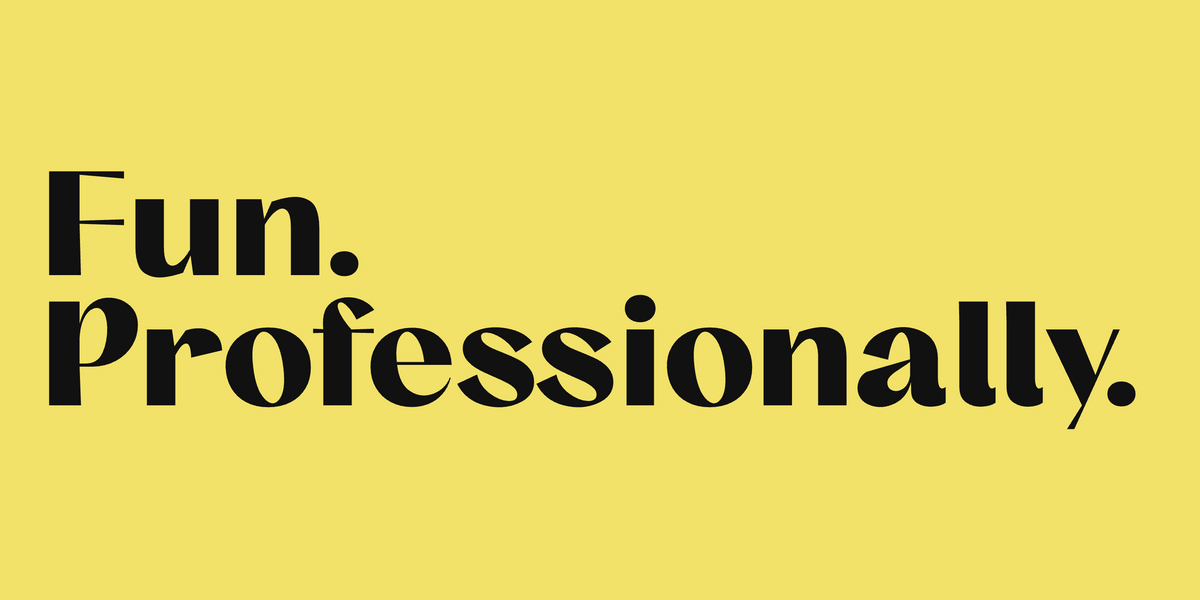
10 fuentes divertidas para proyectos creativos con una personalidad alegre
Fun. Professionally. Set in Rati by Mojomox
Las letras puntiagudas en una fuente pueden parecer más divertidas.
1. Bool, fuente puntiaguda y en negrita
La tipografía Bool es diferente de las fuentes divertidas habituales. A primera vista, este tipo de letra parece relativamente geométrico, pero veámoslo más de cerca.
Algunos de los contadores de la fuente están desplazados, por ejemplo, los contadores de la letra B están más cerca del centro y de la derecha, lo que le da un aspecto un poco bizco y divertido. Las barras transversales del medio son más delgadas que el ancho total del trazo, lo que le da al tipo un carácter de dibujo animado muy atractivo.
Algunos ejemplos son las letras G, E y F. Por último, la barra transversal de la A es más baja de lo habitual, lo que la convierte en una tipografía agradable. Estas divertidas características son más pronunciadas en los grosores de fuente más negrita, desde SemiBold hasta Black.
Las letras que terminan en un trazo ascendente parecen más amigables.
2. Fuente de encaje, estilo de escritura monolineal
Lace es una tipografía de estilo manuscrito. Los grosores de fuente más finos, como ExtraLight y Light, tienen una calidad de bolígrafo, mientras que los estilos más atrevidos presentan un trazo estilo marcador.
Cada letra se dibuja en una línea (estilo monolineal) creando divertidos bucles.
Muchas de las letras de este tipo de letra terminan en un trazo ascendente que crea una apariencia amigable.
También hay disponible una versión redondeada de esta fuente, Lace Rounded.
Las letras que tienen una forma ligeramente diferente a la normal se destacan y parecen más divertidas.
3. Sway, fuente futurista ondulada
La fuente Sway es un alfabeto completo en letras mayúsculas únicamente. Este tipo es excelente para textos de carteles, pero no es particularmente fácil de leer como cuerpo de texto. Sway tiene un estilo futurista y moderno, pero al mismo tiempo se ve moderno y divertido. Las letras de Sway están dispuestas en ángulos particulares, lo que les da un patrón de diseño que las hace fáciles de usar para logotipos.
Las formas redondas en una fuente son más divertidas.
4. Ratón, tipo divertido de estilo acuático.
Vole es una tipografía en mayúsculas y minúsculas, que incluye el alfabeto latino extendido. Su característica principal de diseño son los redondeos que permiten que los trazos se fusionen entre sí, lo que le da al tipo un toque de tinta.
En general, se trata de una fuente geométrica con una estética tipográfica Bauhaus. Por ejemplo, a las letras b, g, n y r les faltan los trazos generalmente extendidos, lo que le suma un toque redondeado y divertido a toda la tipografía.
Vole es ideal para la marca de los niños y es especialmente lindo cuando se escribe todo en minúsculas.
Los puntos i más grandes brindan una sensación amigable
5. Bau, fuente modular redondeada
La fuente Bau es la fuente predecesora de Vole (ver arriba). Las letras de la tipografía se basan en círculos, lo que le da un carácter modular y divertido.
Sus i-dots son más grandes que los puntos estándar, lo que aumenta la facilidad de uso del diseño. Consulta todos los tamaños de fuente, desde superdelgados hasta muy gruesos, aquí .
Las fuentes con apariencia manuscrita son más divertidas.
6. Skay, fuente de burbuja en mayúsculas
Skay es otra fuente de estilo manuscrito que viene en nueve grosores. En particular, sus grosores más audaces se consideran divertidos y amigables, además de tener una personalidad orgánica. Un ejemplo famoso que utiliza este tipo de fuente es el logotipo de Skims.
Este tipo solo tiene letras mayúsculas y números y es parte de la familia de fuentes de burbuja .
Diferentes fuentes
7. Slye, fuente divertida con corte central
Este tipo de letra no es fácil de leer como texto, pero es genial y diferente. Una fuente como Slye es ideal para logotipos, carteles y titulares. Muestra una personalidad que quiere ser audaz y destacarse.
Es divertido mezclar esta fuente con otra. Por ejemplo, si quieres que una letra específica destaque más o que comunique un aspecto de “estar dividido” o “ser diferente”, entonces esta es una opción original.
Las fuentes de contraste inverso dicen “diferente”
8. Puchero, sin tipografía de contraste inverso
Las fuentes de contraste inverso se han vuelto populares en los últimos cinco años y Pout es parte de esa categoría de diseño de fuentes. Las fuentes de contraste inverso son aquellas cuyos trazos son más gruesos en el eje horizontal; por lo general, es lo opuesto y los trazos verticales son más audaces.
El diseño invertido le da a esta fuente un aspecto peculiar, lo que la convierte en la elección perfecta para logotipos y títulos divertidos.
trazos finos y gruesosUna sola letra divertida puede hacer que toda la fuente sea más divertida.